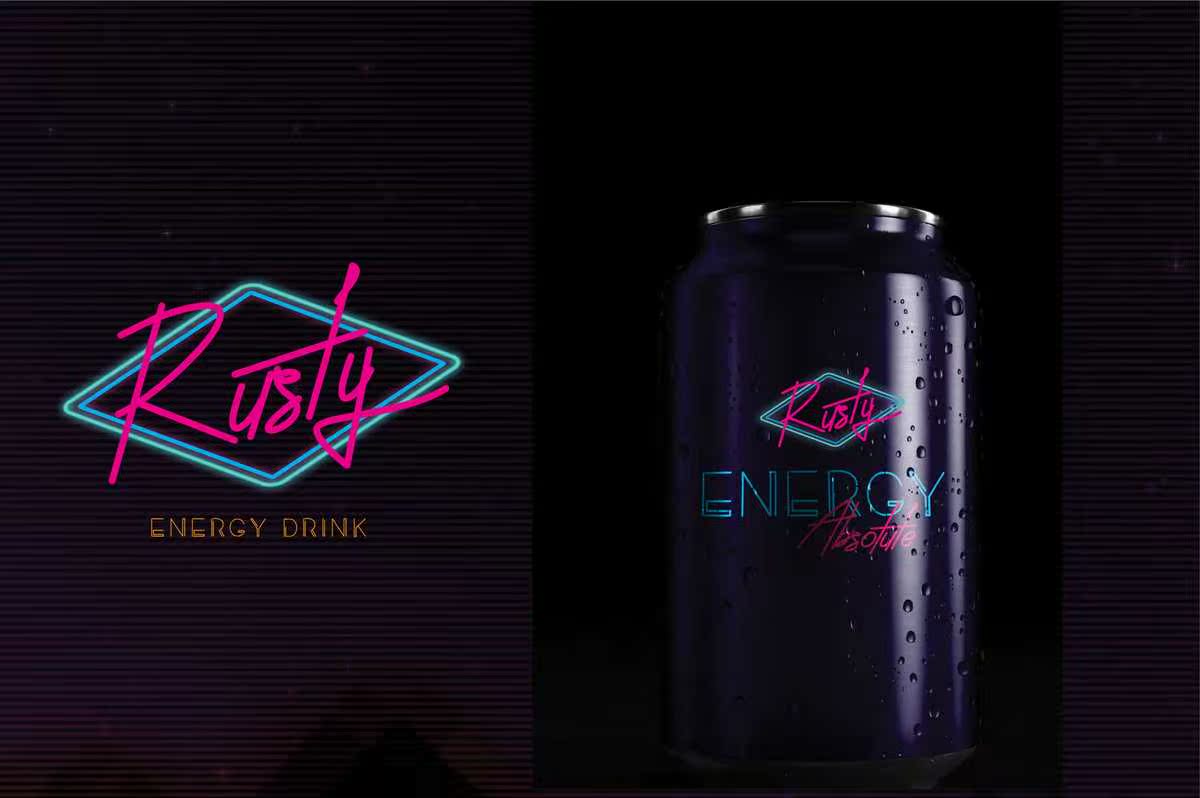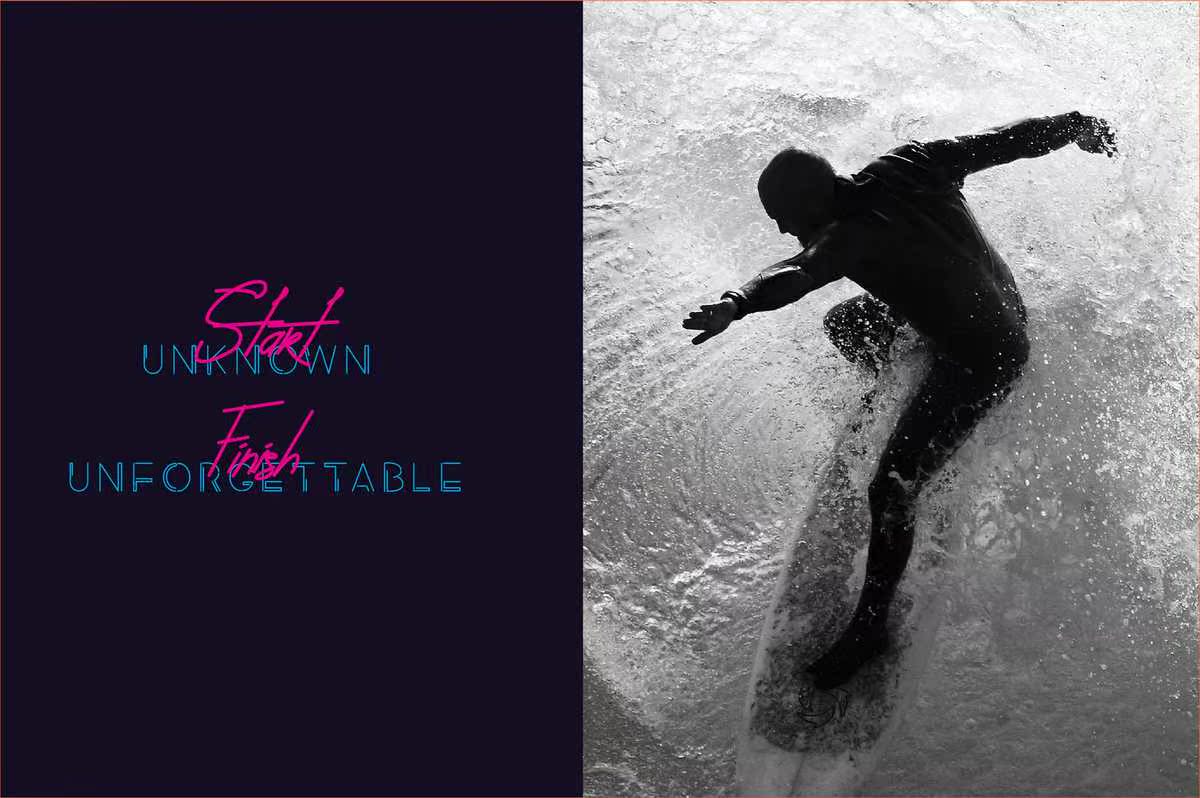
新溶质!受1980年代和Neonlights的启发,aclassy,同时使用脚本和SansFonts。NeonAbsolute为各种设计项目(包括徽标和品牌、社交媒体、广告和产品设计)提供精美的图形协调。您的下载将收到3Font文件,设计为WorkAspectCompanions或简化为强大的标准字体。亮点:NeonAbsolute!受1980年代和NeonLights的启发,NeonAbsolute为各种设计项目(包括徽标和品牌、社交媒体、广告和产品设计)提供了精美的图形协调。您下载时将收到3FontFiles,设计为Ork Aspect Company或简单的标准字体。亮点: